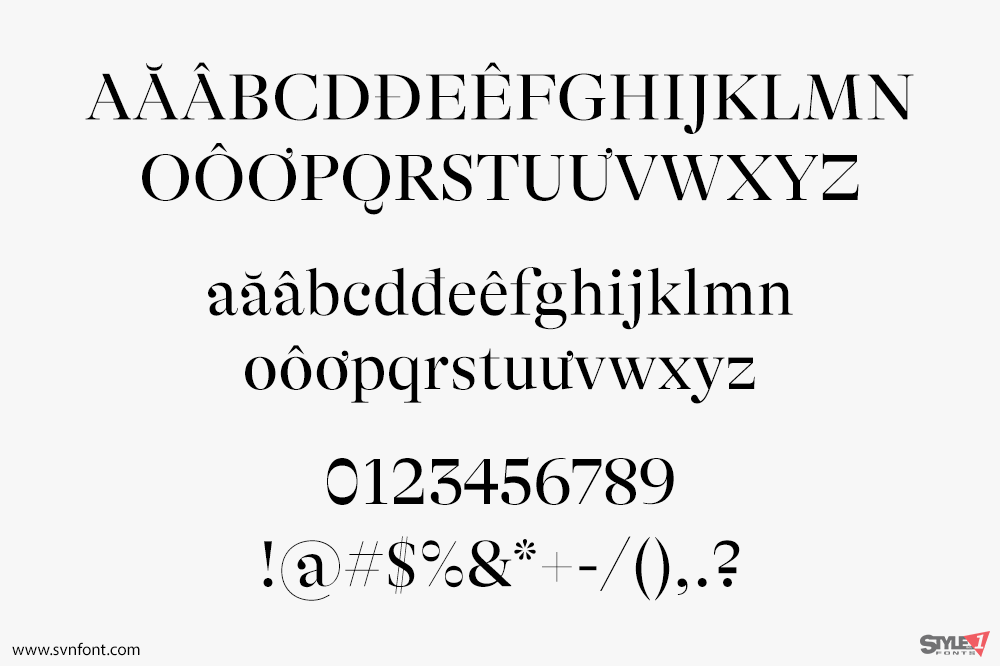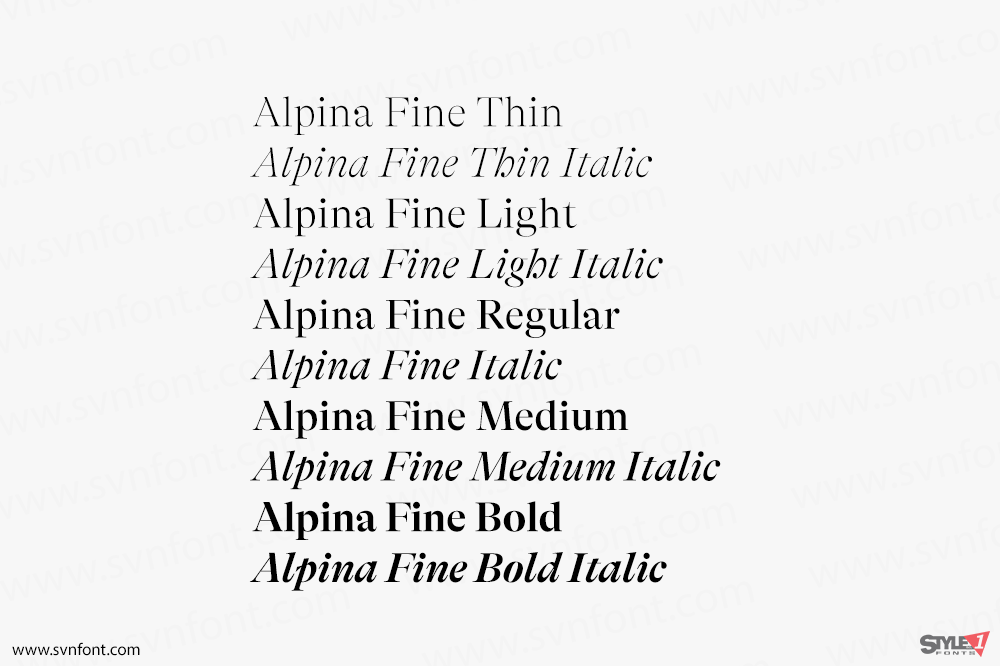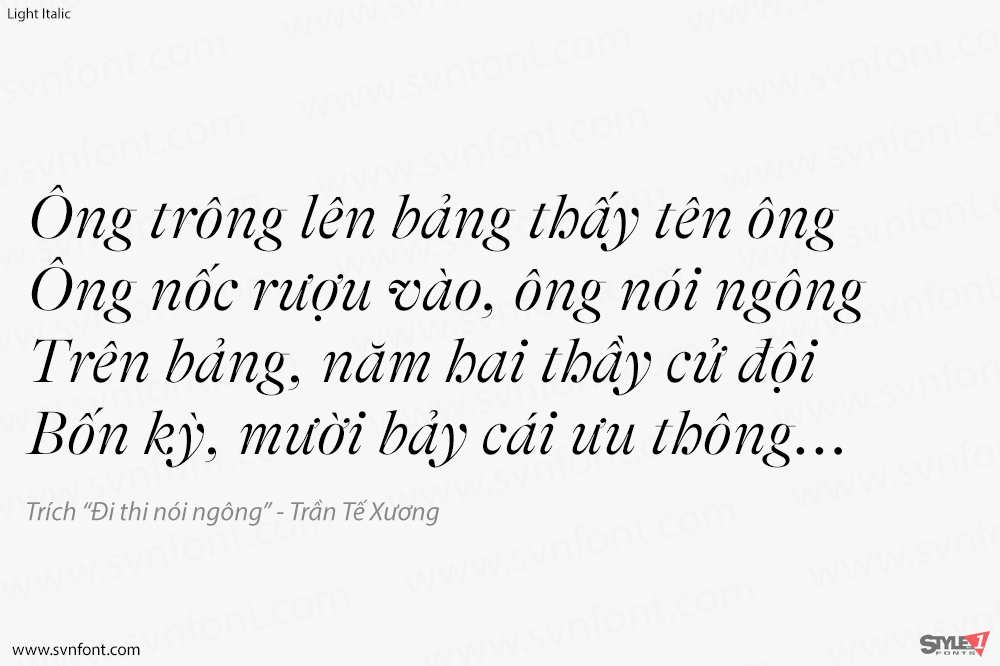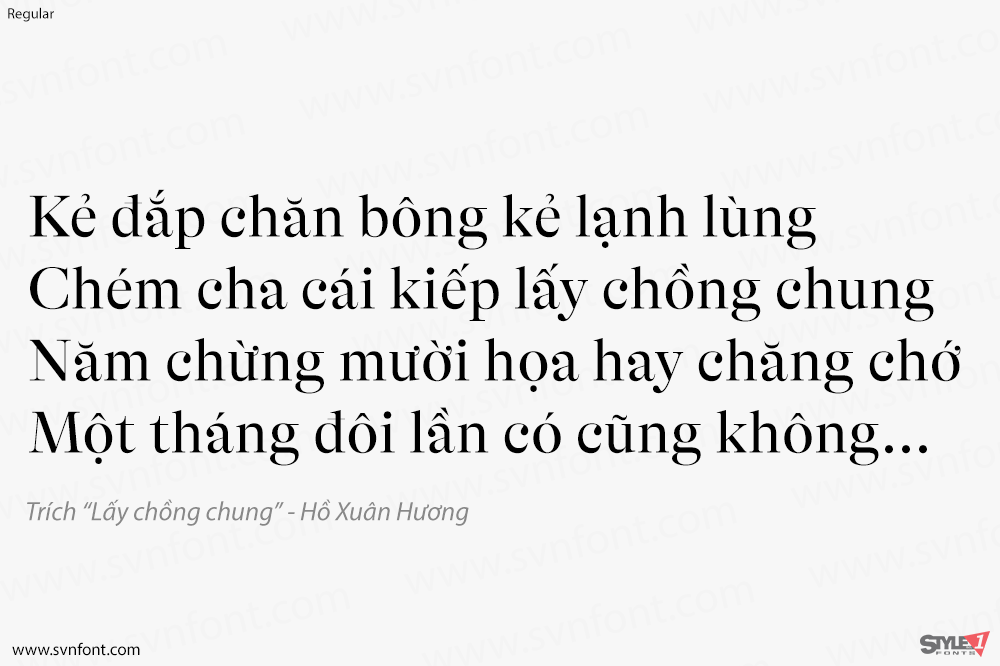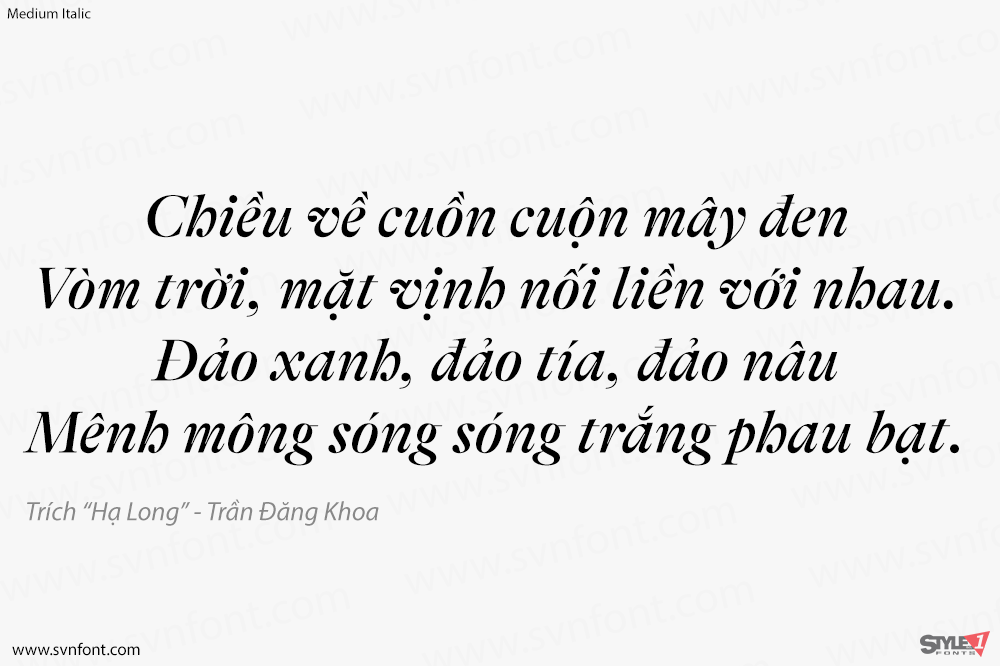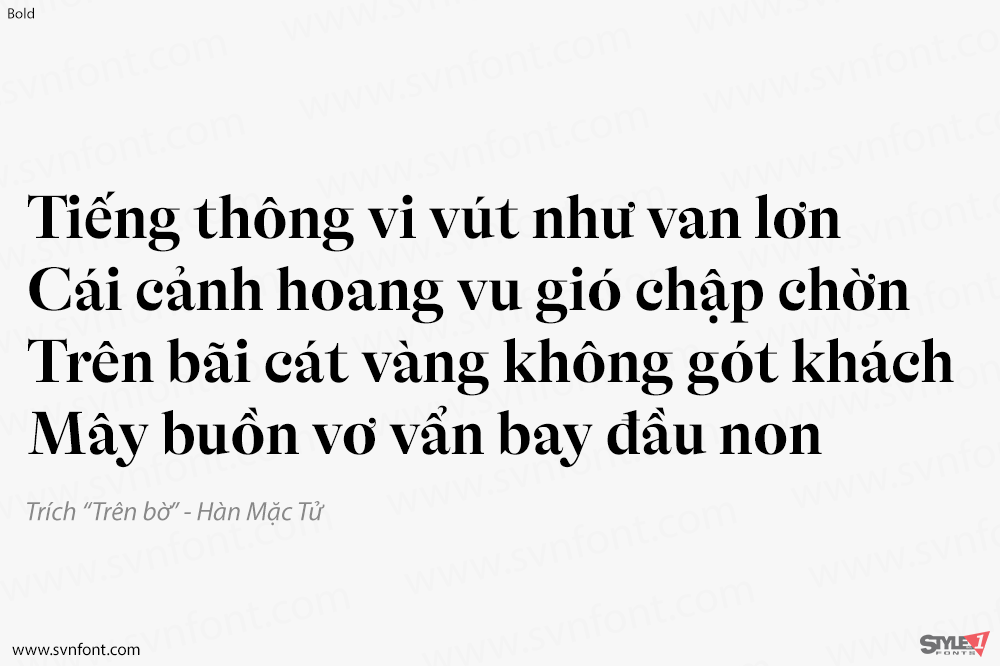
GT Alpina tự hào gọi mình là một kiểu chữ serif “workhorse” (đa dụng, mạnh mẽ), nhưng lại thích thú chơi đùa với chính ý nghĩa của khái niệm đó. Nó lục lọi trong kho tàng lịch sử kiểu chữ để hồi sinh những hình dạng mà một số người có thể lầm tưởng là quá biểu cảm, dẫn đến một họ phông chữ tỉ mỉ kết hợp những hình dạng riêng biệt này với một cách thể hiện thực dụng.
Nhà thiết kế: Reto Moser
Nhà phát hành: GrillType